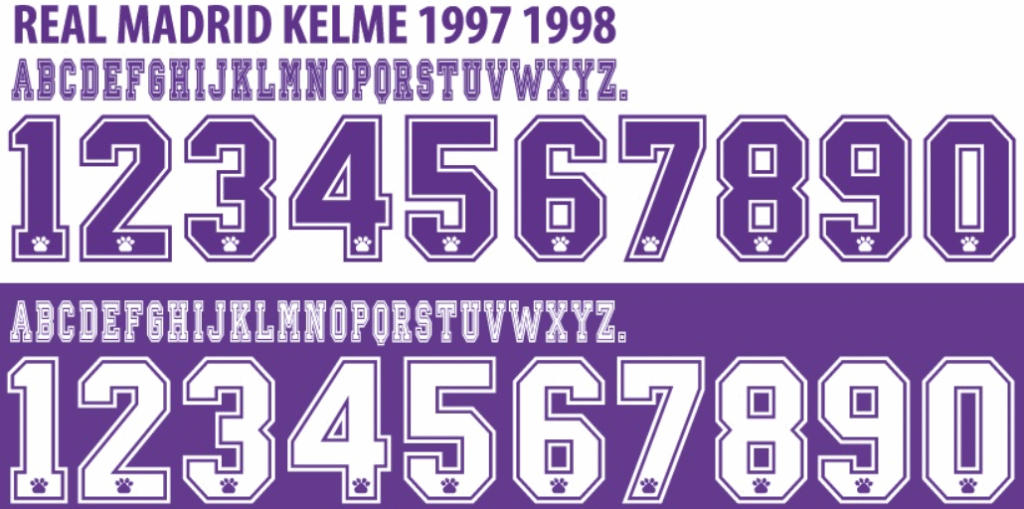
Viaje no tempo direto para a temporada que mudou a história moderna dos Merengues. A temporada 1997-1998 não foi apenas mais um ano; foi o momento em que o Real Madrid quebrou um jejum de 32 anos para conquistar a Europa novamente.
Neste post, trazemos a fonte lendária utilizada pela fornecedora Kelme no uniforme que consagrou craques como Raúl, Roberto Carlos, Seedorf e Mijatović na conquista da inesquecível “La Séptima” Champions League.
Este arquivo foi digitalizado com precisão para garantir que suas réplicas e projetos de design mantenham a essência retrô original.
- Conteúdo: Alfabeto completo e numeração oficial da época (estilo 3D sombreado).
Estilo Visual e História
A tipografia criada pela espanhola Kelme para esta temporada é um clássico dos anos 90. Diferente das fontes minimalistas atuais da Adidas, este estilo possui uma personalidade robusta e tridimensional.
Os números apresentam um efeito de “sombra projetada” (shadow block), muito comum na década de 90, o que dá volume e destaque à numeração nas costas da camisa branca. As letras seguem um padrão serifado sutil, transmitindo a realeza e a tradição do clube espanhol. É a fonte exata usada na final contra a Juventus em Amsterdã.